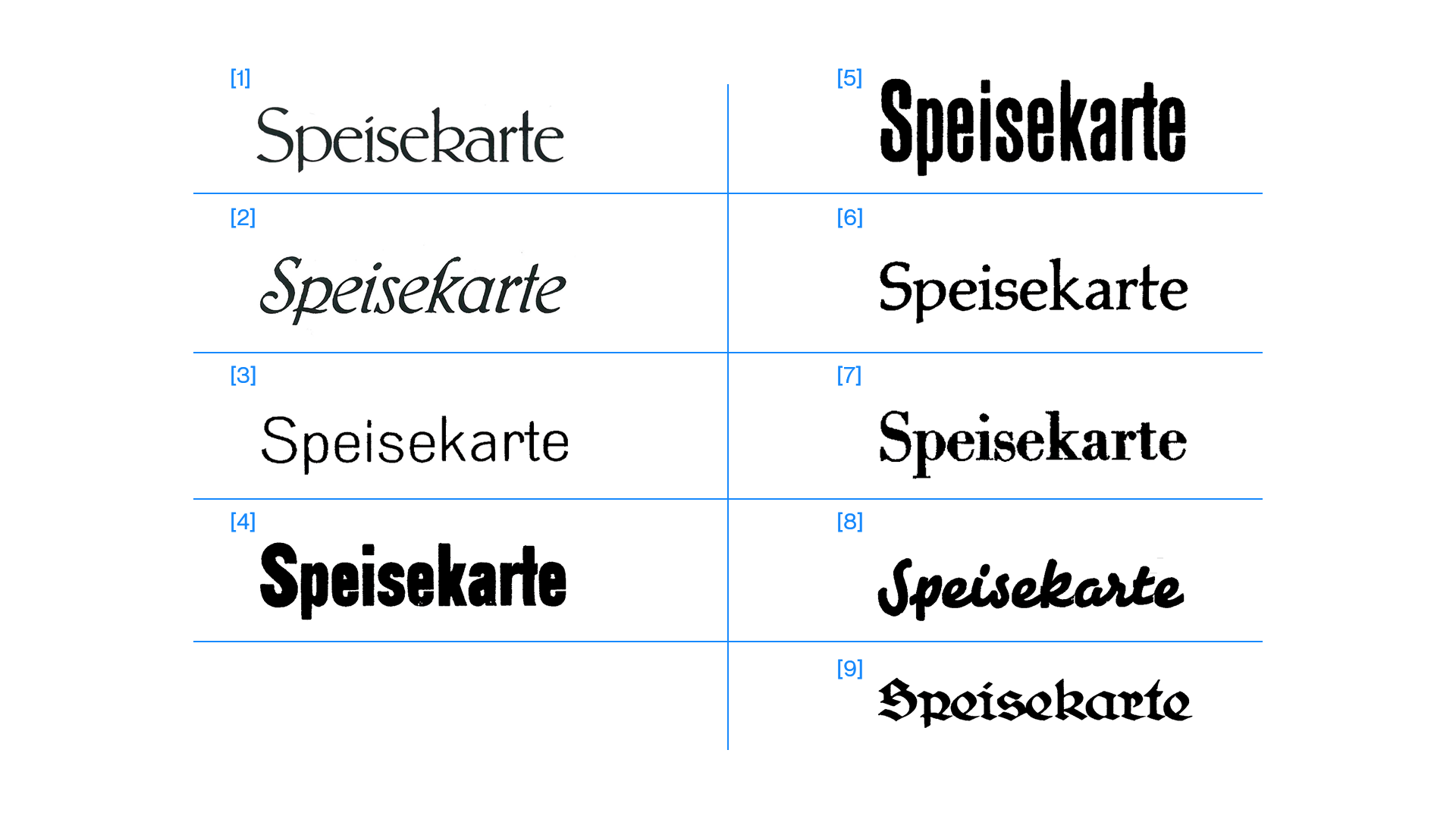
Webfont Lizenz von Unbekannten Bleisatzschriften
Hallo Typografen und Schriftgestalter,
Ich wollte wissen inwiefern Schriften dessen Namen und Herkunft nicht genau bekannt sind digitalisert und im Web genutzt werden dürfen, ohne direkt als Plagiat zu gelten?
Ein Kunde hat mehrere Bleisatz-Schriften die er nun in einer Webapplikation als Druckvorschau für den Endnutzer veranschaulichen will.
Einige Schriften ließen sich eindeutig bekannten Schriften zuordnen (bspw. Garamond) andere wiederum nicht.
Schrift-Lizenzierung scheint nach eingängiger Recherche ein komplexes Thema zu sein, besonders im Web.
Der BeitragSind Fonts Software von Ralf Hermann (Siehe "Schöpfung durch Digitalisierung") zeigt zumindest auf das auch antike Schriften nicht ohne weiteres Kopiert werden sollten.
Im Falle der genannten Garamond Schrift ist klar, hier muss der Kunde eine Webfont-Lizenz erwerben. Bei den unbekannten Schriften (Die ich bereits mit Tools wie WhatTheFont untersucht und verglichen habe) frage ich mich jedoch, inwiefern diese nachgestellt werden dürfen. Gibt es Ausnahmen für eben jenen Anwendungsfall ,wo lediglich eine Vorschau des finalen Drucks mit den jeweiligen Schriften benötigt wird? Zählt das transformieren dieser Schriften in eine Webfont, über das einfache Vektorisieren von Buchstaben hinaus, bereits unter den Begriff: Geschmachsmuster (Falls Jener in diesem Kontext überhaupt Sinn ergibt 😛 )und somit als eigene "kreative" Schöpfung?
PS: Falls jemand noch weitere Seiten und Dokumente bzgl. Gesetze zur Nutzung und Erstellung von Schriften hat würde ich mich auch darüber sehr freuen.
PPS: Im Anhang sind die Schriften welche ich leider nicht zuordnen konnte. 😜
So schwierig ist das in der Praxis zum Glück nicht. Du darfst praktisch¹ jede Bleisatzschrift »digitalisieren«, also nachzeichnen und aus diesen Zeichnungen einen Font machen. Das Geschäftsmodell vieler, absolut seriöser Schrifthersteller beruht darauf, alte Schriften (anderer Gestalter) ohne die Entrichtung irgendwelcher Lizenzgebühren und ohne explizite Erlaubnis zu digitalisieren und diese Fonts dann als eigene Werke zu verkaufen.
Was du ohne Erlaubnis nicht darfst, ist, existierende Fontdateien einfach zu kopieren oder zu verändern. Also ganz kurz: solange du keine Fontdateien (Software) »anfasst«, bist du bei der Digitalisierung von Schriften praktisch immer auf der sicheren Seite. Das betrifft auch Schriften, die bereits digitalisiert wurden. So gibt es über ein Dutzend kommerziell vertriebener Garamond-Versionen, alles völlig legitim. (Und es gibt kostenlose, die du ohne Entrichtung von Lizenzgebühren auch als Webfonts benutzen darfst.)
1. Theoretisch könnte es Schriften geben, die auch für Laien erkennbar so neu und außergewöhnlich sind, dass ihr Abbild eben nicht frei verwendet werden darf. Aber praktisch ist das kein Thema, schon gar nicht bei Schriften, die so alltagstauglich waren, dass sie in Blei gegossen wurden.
Wenn du als Musterwort statt Speisekarte das Wort Hamburg (oder Hamburgefons) genommen hättest, wären die Schriften im Seemann leichter zu finden.
Und um die richtigen Auslassungen von Þorsten zu ergänzen: Manchmal kann es vorkommen, dass Schriftenanbieter sich die Namen der alten Bleisatzschriften als Marke gesichert haben. Da reicht es dann einfach für die eigene Digitalisierung eben einen neuen, durchaus ähnlichen Namen zu erfinden. Anders ist es im übrigen auch in der Bleisatz-Zeit gewesen, da haben Schriftgießereien nicht selten erfolgreiche Schriften der Konkurrenz nachgezeichnet und geschnitten, und haben sie dann unter eigenem Namen vertrieben.
Auch Schriftnamen aus der Bleisatz-Zeit dürfen nicht wiederverwendet, wenn die ursprünglichen Hersteller bzw. Rechtsnachfolger die Namen als Trademarks (Markenzeichen) angemeldet haben. Kurz: Eine neue Schrift auf Basis der Bleisatz-Palatino dürfte man m.W.n. durchaus zeichnen und veröffentlichen. Aber Monotype würde es als Markenverletzung betrachten, wenn die Font so vermarktet wäre, dass das Wort Palatino in der Name wäre. Auch u.U., wenn man in Beschreibungstexte angeben würde, die Schrift sei von der Palatino inspiriert. Nur als Beispiel.
Aber etwas entfernt ähnliches, wie z.B. Paladin könnte gehen (sofern es die nicht auch schon gibt, müsste man prüfen. Beispiele für so ein Vorgehen gibt es ja reichlich, ich denke da z.B. an die CorelDraw-Versionen vieler bekannter Schriftarten.
Ach so, die hier beispielhaft genannte Palatino gibt es auch unter diesen Namen:
Aldus, Palatino nova, Book Antiqua, Palladio, Palazzo, Zapf Calligraphic 801 und  Parlament
Ich nehme an, dass Aldus, Paladino nova und Book Antiqua alle eingetragene Marken von Monotype sind  (bzw. Aldus und die ganzen novas wären von Linotype angemeldet würden, bevor Linotype von Monotype übernommen wurde). Da Monotype Bitstream auch kaufte, wäre Zapf Calligraphic 801 auch jetzt eine Monotype-Schrift, wobei eine solche Name wahrscheinlich unschutzbar ist.
Sind die Schriften aber mindestens um die 100 Jahre alt, sehe ich die Digitalisierung wiederum als löbliche Rettungsaktion an, mit der mit niemandem mehr auf die Füße treten kann.
Ein Umstand, auf dem ein nicht unbeträchtlicher Teil meines Lebensunterhaltes beruht 🙂